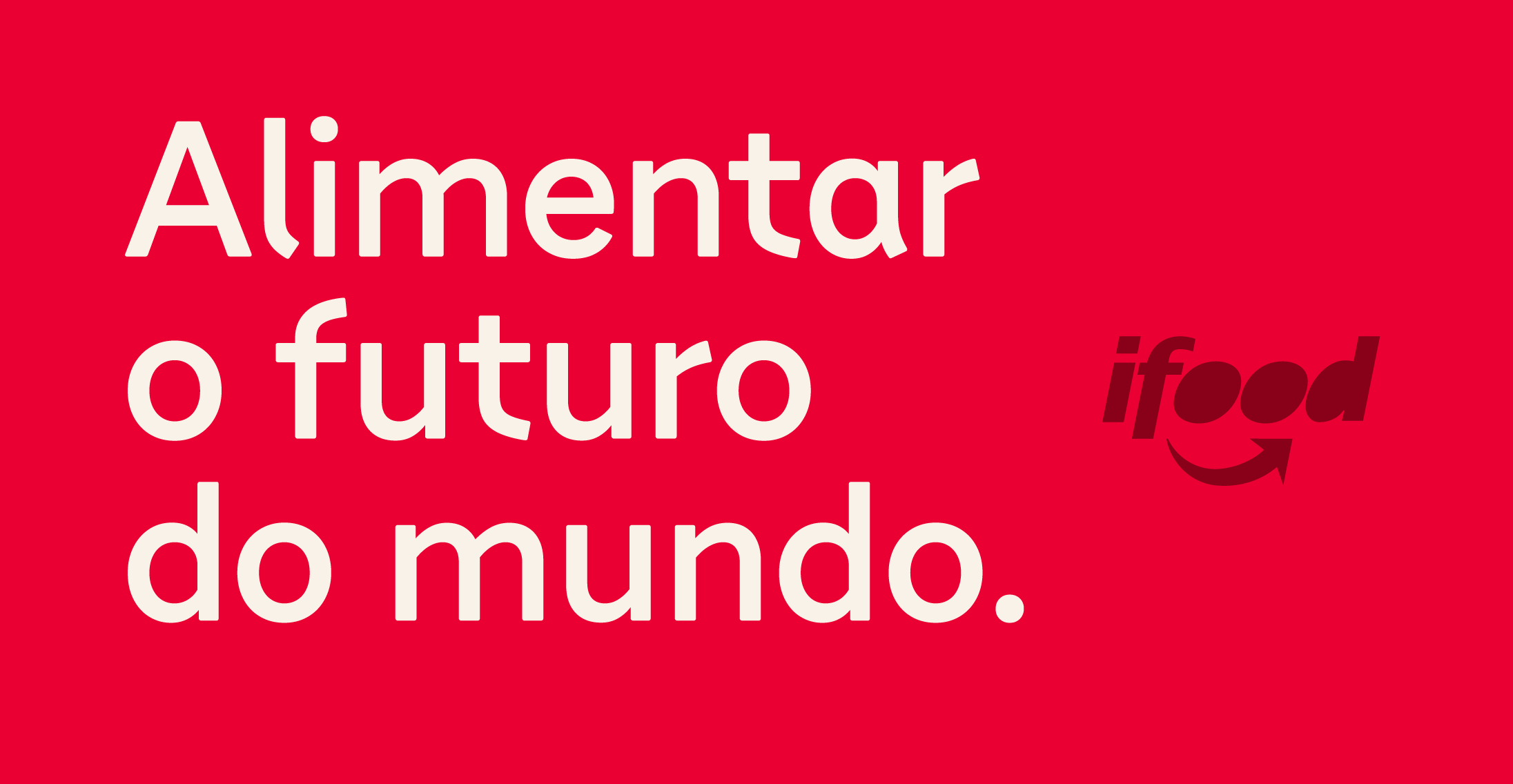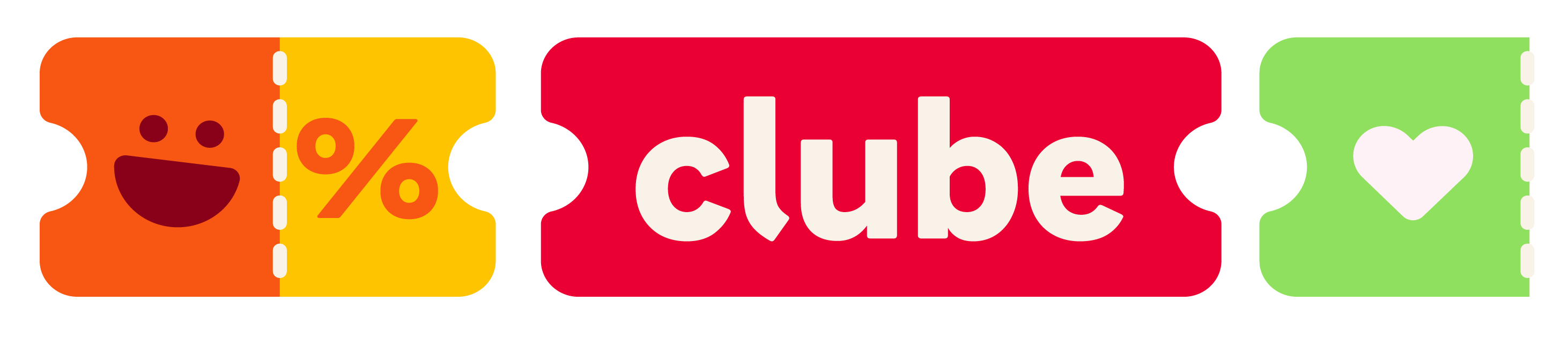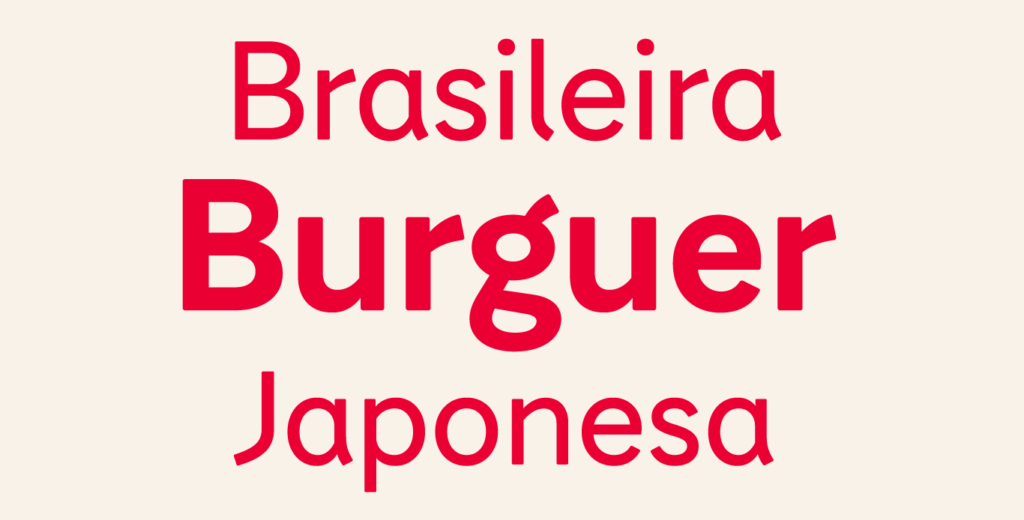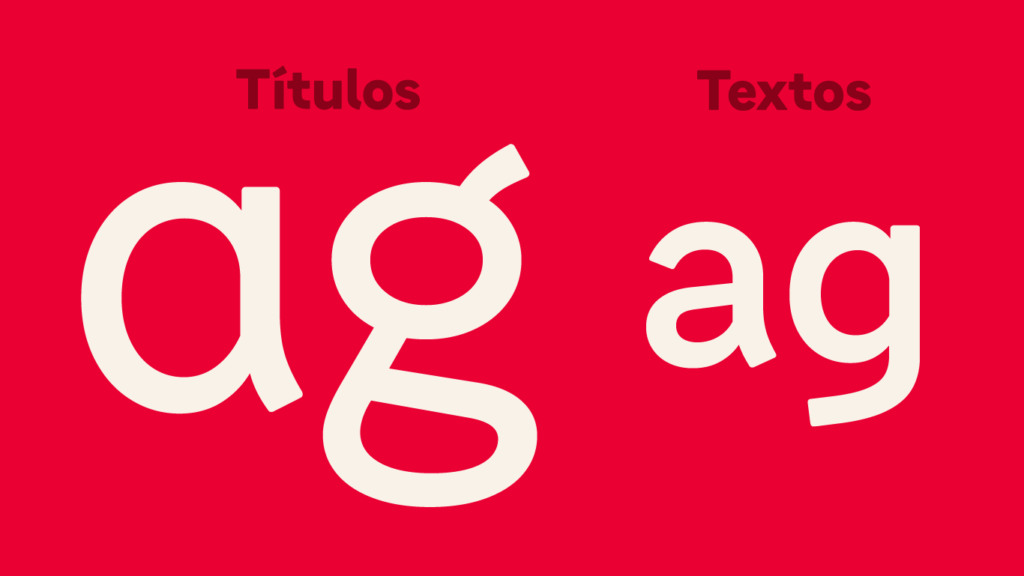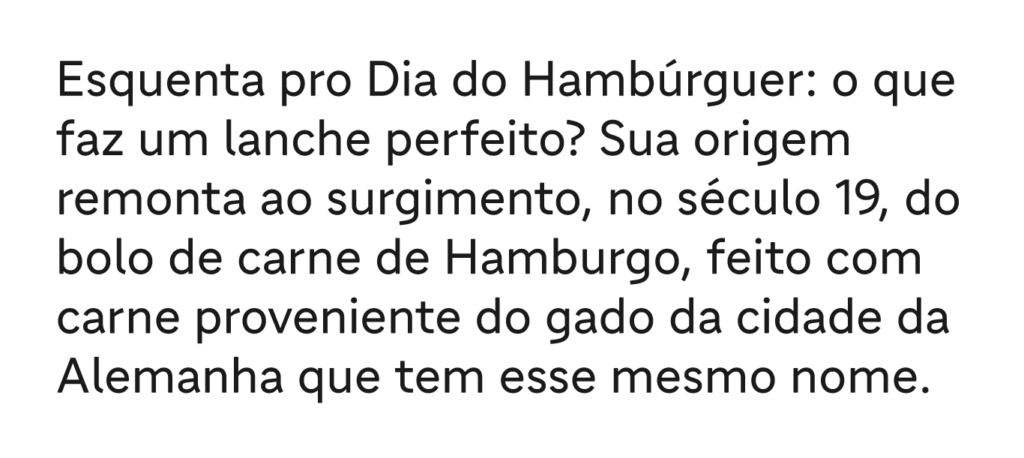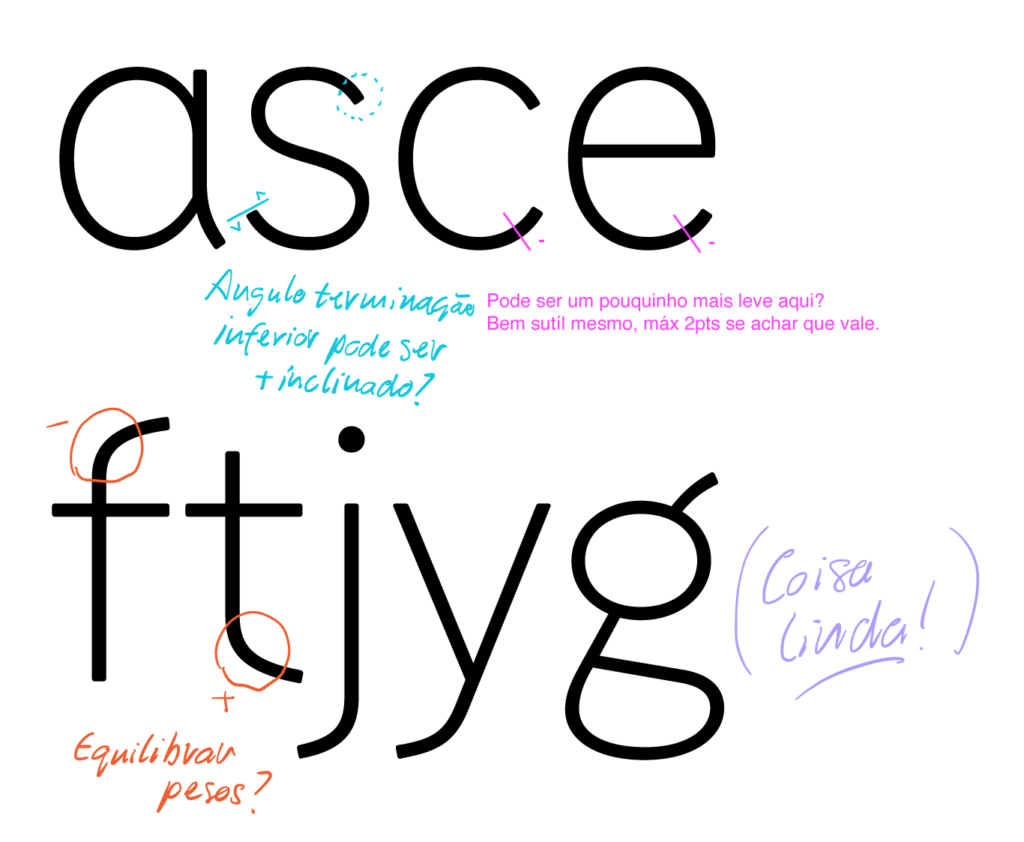
Um pedido muito especial preparado para e com o iFood
Quando falamos de tipografia para produtos digitais, é comum cairmos em fontes genéricas; muito funcionais, e por conta disso, convencionais. Mas quando o app é a principal forma de relacionamento com a marca, ele precisa também entregar uma personalidade própria para consolidar sua identidade.
Qual a quantidade certa de tempero para esta receita? É preciso chamar todos para a cozinha, e foi isso o que fizemos para o iFood, juntos com a FutureBrand São Paulo.
A colaboração é mais do que um valor na nossa cultura, é uma prática que assegura o sucesso dos projetos. Antes de qualquer traço, reunimos lideranças de diversas áreas do iFood, a agência Suno e a FutureBrand, para uma dinâmica estruturada de duas horas. Nesta imersão, ouvimos as dores ao utilizar as fontes anteriores sob diferentes perspectivas. Além disso, encontramos os pontos de convergência nas expectativas de cada um, o que possibilitou construirmos juntos os critérios de sucesso do projeto para que ele atendesse a toda a organização.
Ser uma identidade reconhecível através da tipografia. Uso consistente, aproximando o produto e a comunicação. Com estas premissas, apresentamos 11 ideias tipográficas — palavras-chave no peso Regular — para avaliação em conjunto.
Com os sliders de personalidade acordados na imersão, três ideias apresentaram o potencial para atender os desafios, com ênfases em aspectos diferentes. Expandidos em Conceitos, analisando todos os pesos, o cliente pode tomar uma decisão bem fundamentada sobre as letras que se transformariam no tom de voz visual do iFood.
As formas bem abertas e pouco usuais de letras como ‘f’, ‘t’ e ‘r’ inspiram tecnologia sem trazer a frieza geralmente associada com ela. Além disso, elas conferem distinção (buscando facilitar o reconhecimento de marca) enquanto as outras, mais convencionais, garantem um equilíbrio no conjunto e a leiturabilidade geral (o conforto de leitura). Ainda assim, uma versão específica para textos altera o desenho de letras como ‘a’ e ‘g’ priorizando a legibilidade individual em tamanhos pequenos.
As fontes Tipo iFood geram distinção sem cair em modismos; são autênticas, carregam a personalidade da marca e entregam, na experiência do usuário, os atributos presentes na comunicação.
“Com diversas trocas, workshops e testes, criamos uma tipografia que abraça nosso universo visual e traduz nosso posicionamento, ao mesmo tempo em que é bastante funcional e responde ao nosso desafio de escala.” — Victor Zanini, Head of Design Ops, iFood
“Nosso desafio era não só traduzir o posicionamento para o desenho da tipografia e elementos visuais, mas enxergar em cada letra e palavra o potencial de conexão com os públicos do iFood, equilibrando estética e funcionalidade, encantando em cada detalhe.” — Felipe Luz, Sócio e Diretor, FutureBrand